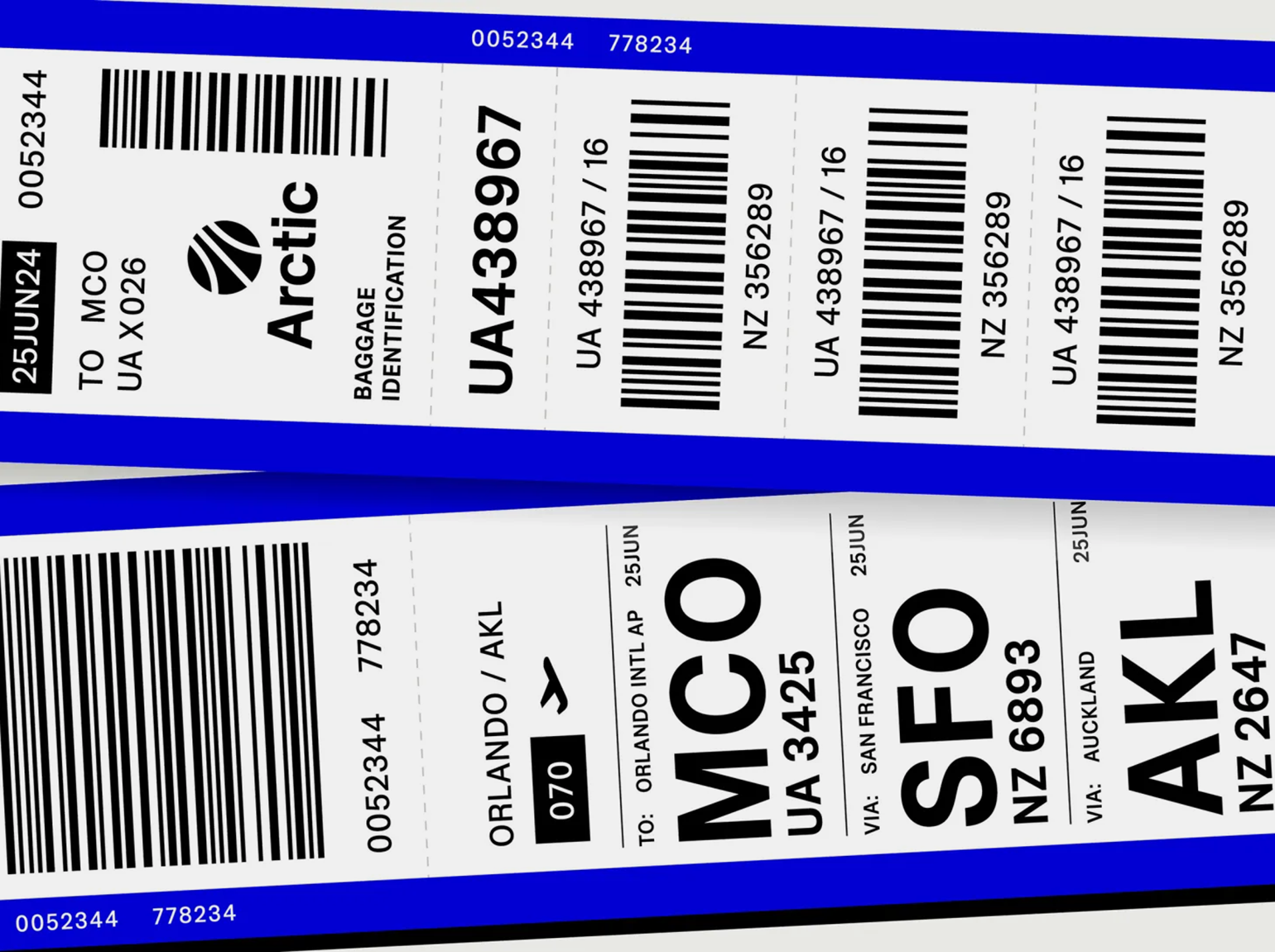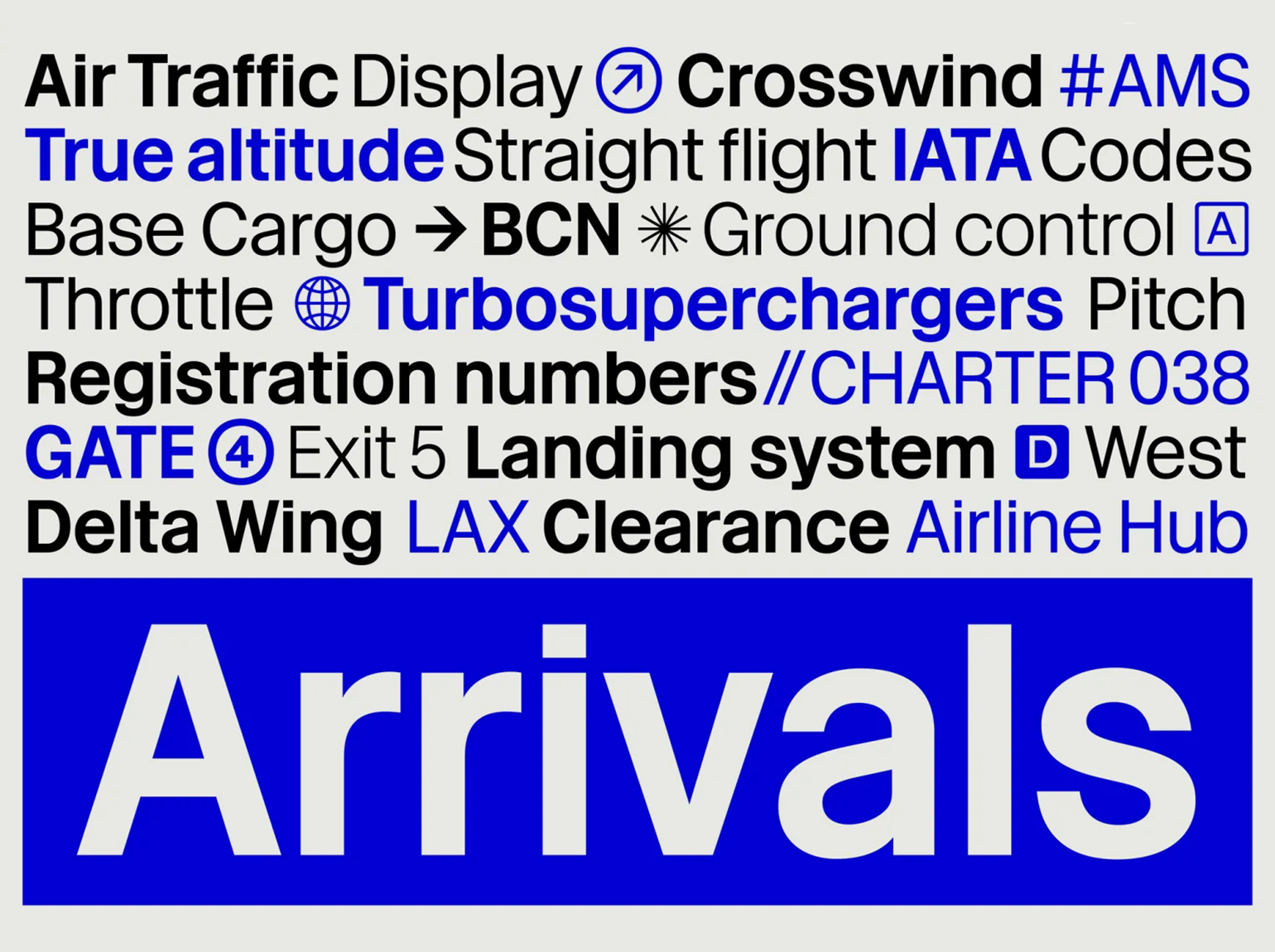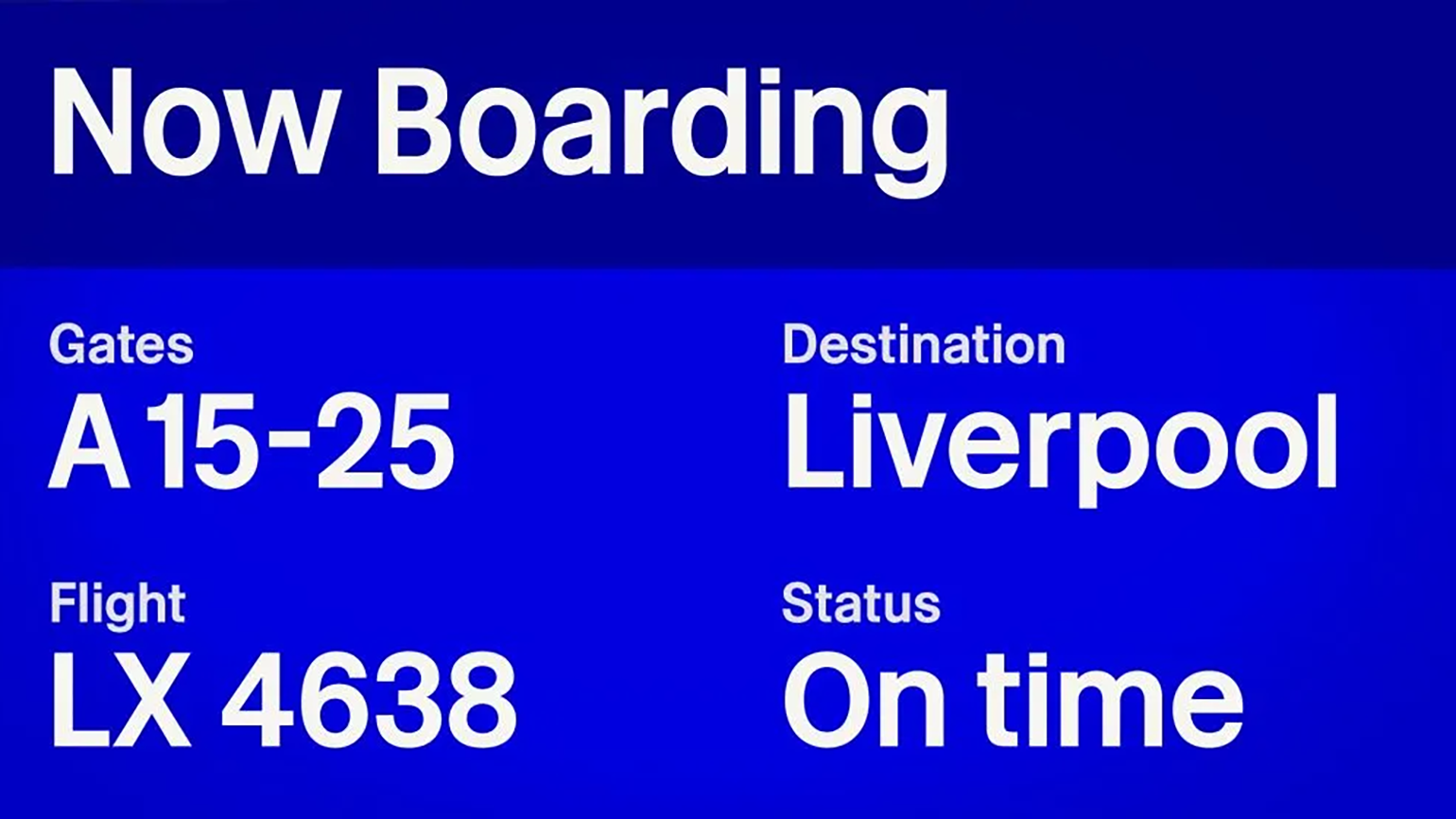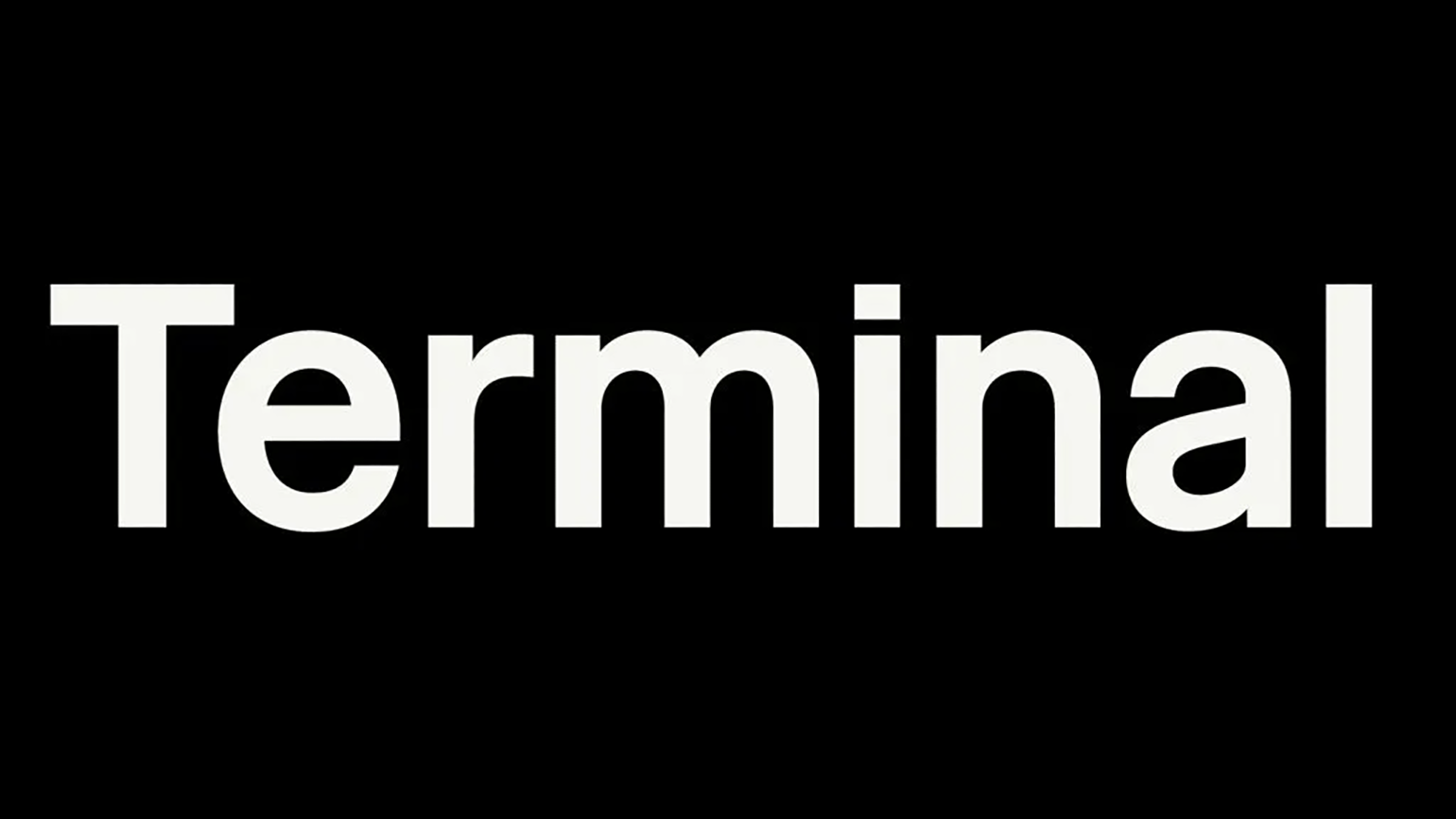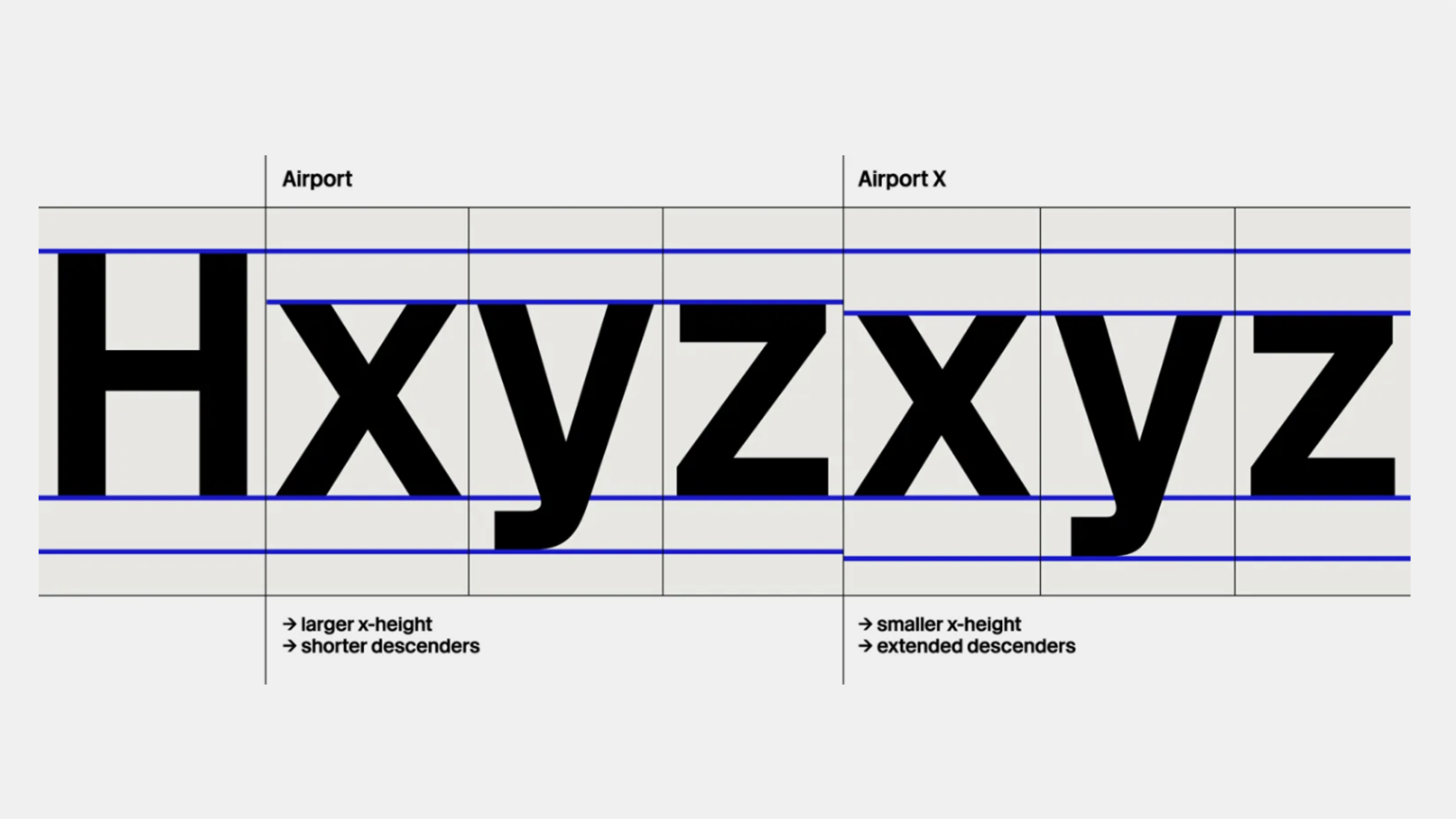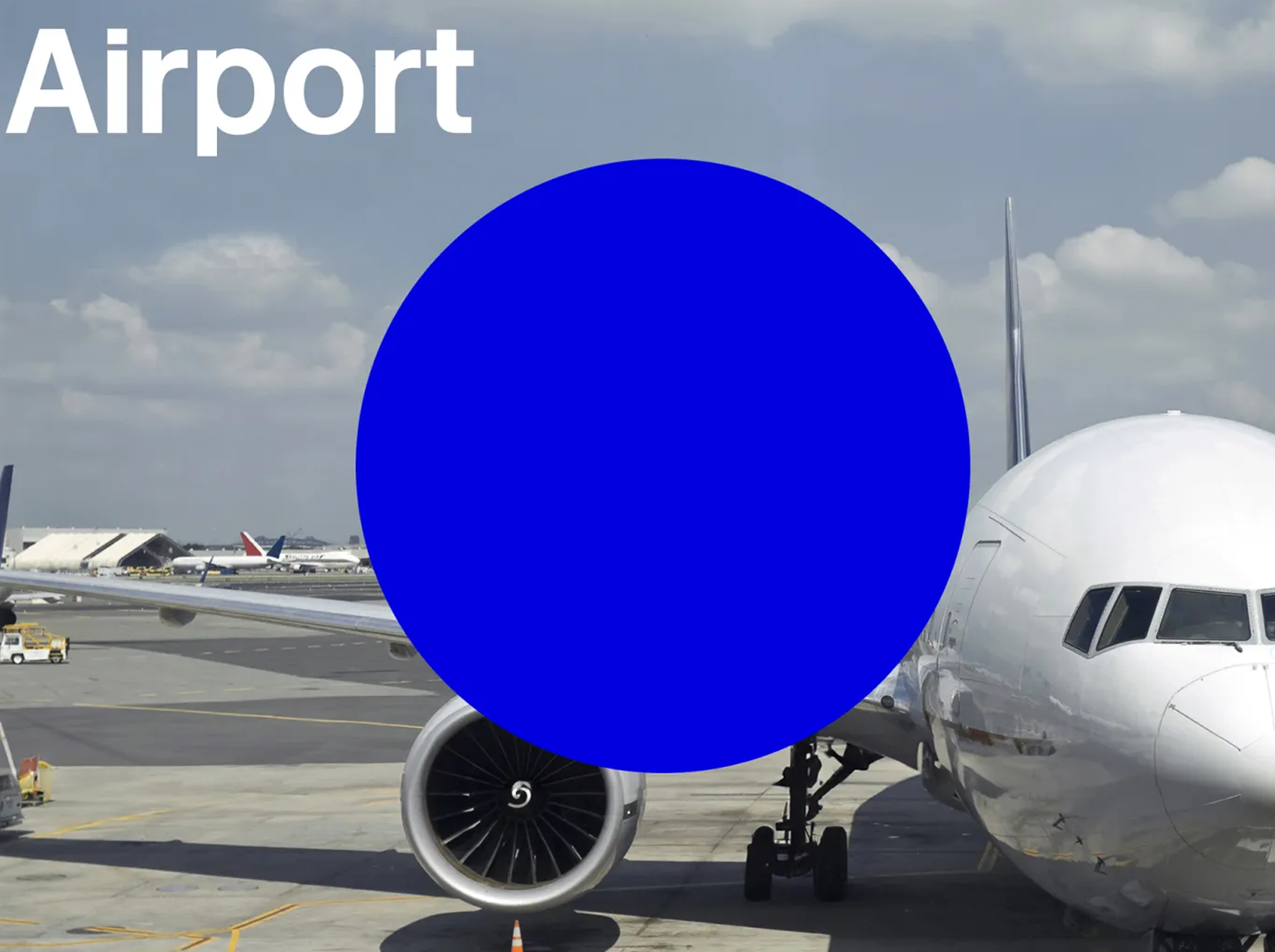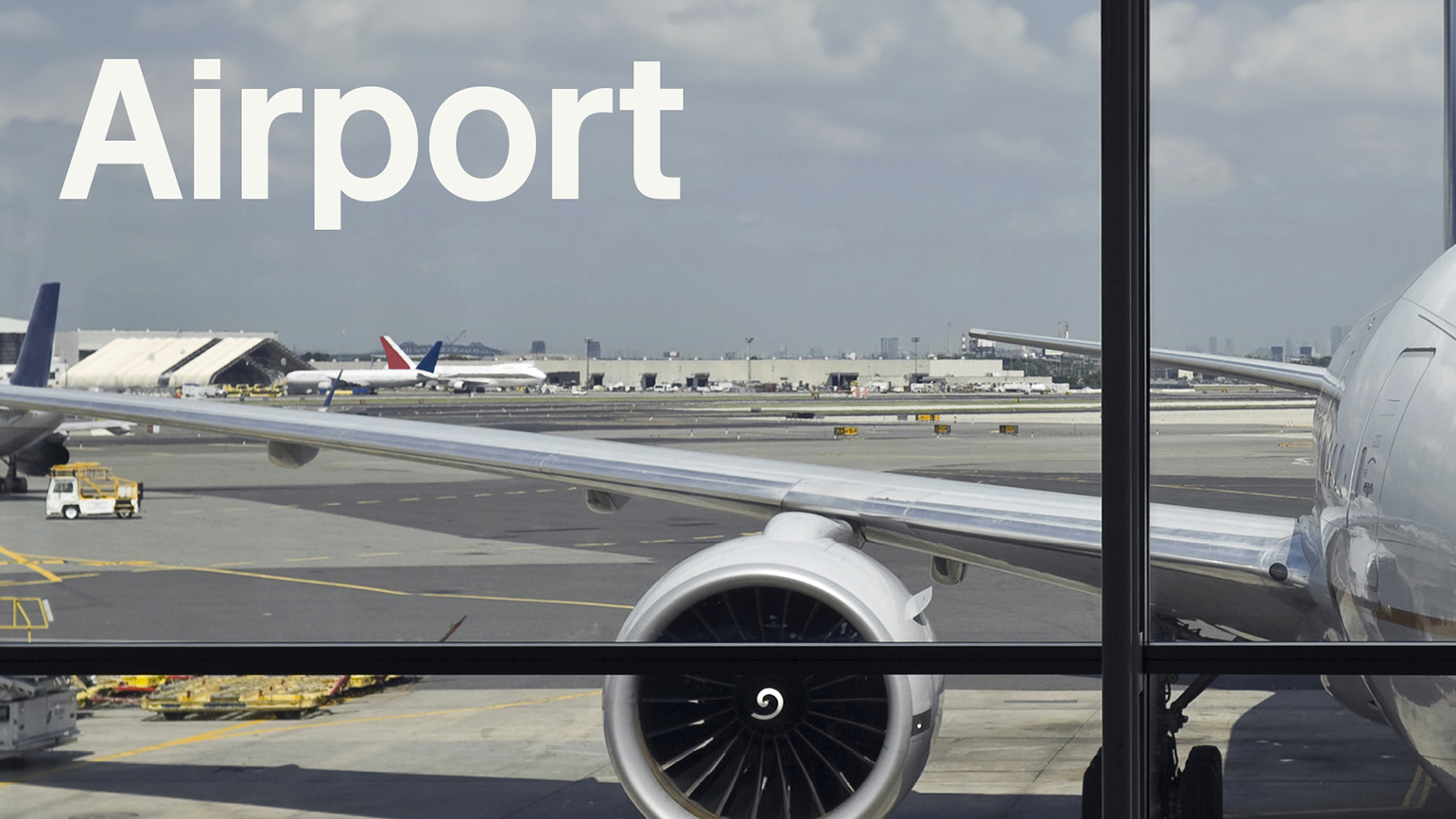
Студия Revolver Type переосмыслила легендарный шрифт Мэтью Картера «Аэропорт»
Его разработали в 1960 году.
Основатель студии Revolver Type Лукас Шнайдер увидел винтажную игру-считалку, выпущенную в 1979 году. Его внимание привлёк шрифт. Он обратился к берлинскому дизайнеру и эксперту Флориану Хардвигу, который выяснил, что это шрифт Airport Spotlight — ответвление от Airport Мэтью Картера, шрифта, разработанного в 1960 году для лондонского аэропорта (ныне Хитроу).
Лукас Шнайдер стал исследовать историю создания указателей аэропорта и нашёл труднодоступную книгу 1970 года A Sign System Manual, написанную Тео Кросби, Колином Форбсом и Аланом Флетчером.
Шрифты Airport и Airport X — это результат его изысканий. Это современная версия культового шрифта Картера через 64 года после его выпуска.
Airport Шнайдера — это не просто прямая оцифровка. Дизайнер изменил пропорции апертуры, модуляцию и X-высоту (это мера высоты строчных букв в одной гарнитуре), что позволило использовать семейство в меньших размерах, чем оригинальная версия. А иконографика напоминает, что оригинальный шрифт использовали для указателей.
По словам Лукаса Шнайдера, в работе он столкнулся с некоторыми сложностями. Например, ему нужно было определить, какая форма строчной буквы r использовалась в оригинальном релизе.
— С другой стороны, это дало мне некоторую свободу действий, чтобы учесть личные вкусы и предпочтения. К счастью, возможности OpenType позволяют включать альтернативные глифы, поэтому я добавил несколько. Однако альтернативные глифы часто используются реже, чем формы по умолчанию, поэтому это решение пришлось тщательно обдумать, — цитирует дизайнера издание Printmag.
По его словам, оживление старых шрифтов — давняя традиция в дизайне и неотъемлемая часть этого ремесла. Оцифровка делает его более доступным и простым в использовании для широкой аудитории.